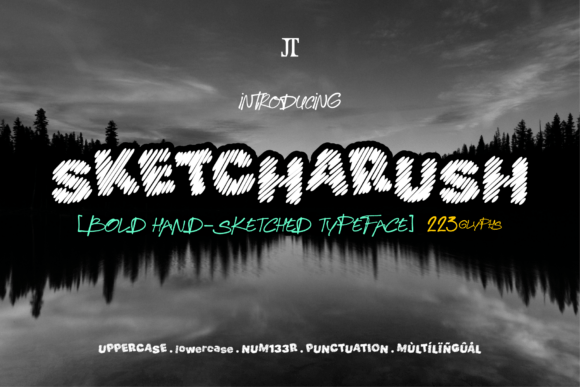
Sketcharush
Если вы ищете высококачественные ресурсы, такие как Sketcharush, этот премиум-пакет — фантастический выбор для ваших творческих проектов.
Созданный с высокой точностью, Sketcharush предоставляет чистые векторы, плавную типографику и коммерческую лицензию для вашего спокойствия.
Создаете ли вы продукты POD (печать по требованию), свадебные приглашения или графику для социальных сетей, Sketcharush станет идеальным выбором.